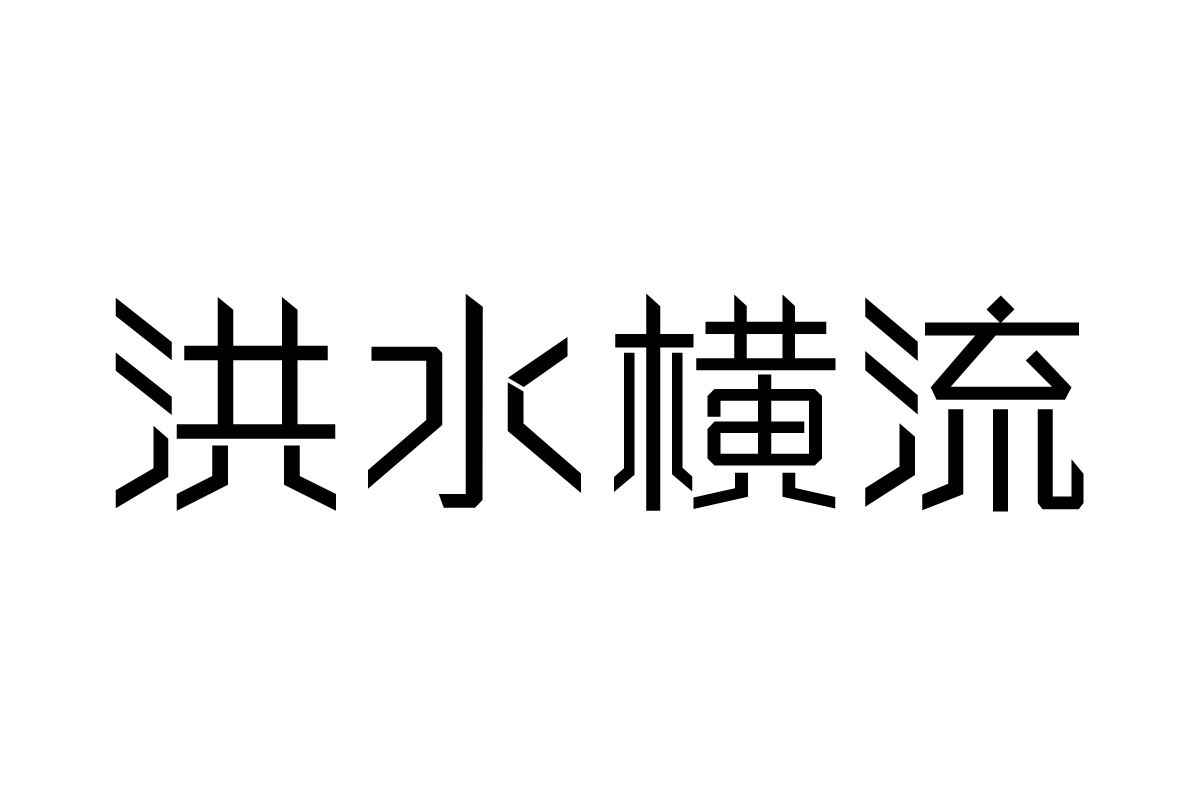
三极芯片体细字体是一种具有独特风格和特点的字体,它以其纤细的笔画、独特的结构和优雅的形态而著称。这种字体的设计灵感来源于传统的三极芯片,因此得名“三极芯片体细”。
三极芯片体细字体的特点如下:
1. 纤细的笔画:这种字体的笔画非常纤细,线条流畅,给人一种优雅、轻盈的感觉。这使得它在视觉上显得更加精致和细腻。
2. 独特的结构:三极芯片体细字体的结构相对简单,但每个字母都经过精心设计,以保持整体的平衡和协调。这使得它在视觉上呈现出一种和谐的美。
3. 优雅的形态:这种字体的形态优美,线条流畅,给人以美感。它的每一个笔画都充满了艺术感,仿佛在讲述一个故事。
4. 适合多种场景:三极芯片体细字体适用于各种场景,如广告、设计、印刷等。它的简洁性和优雅性使其成为许多设计师的首选字体。
总之,三极芯片体细字体以其独特的风格和特点吸引了众多人的喜爱。它不仅能够为设计作品增添一份美感,还能够传达出一种优雅、精致的氛围。